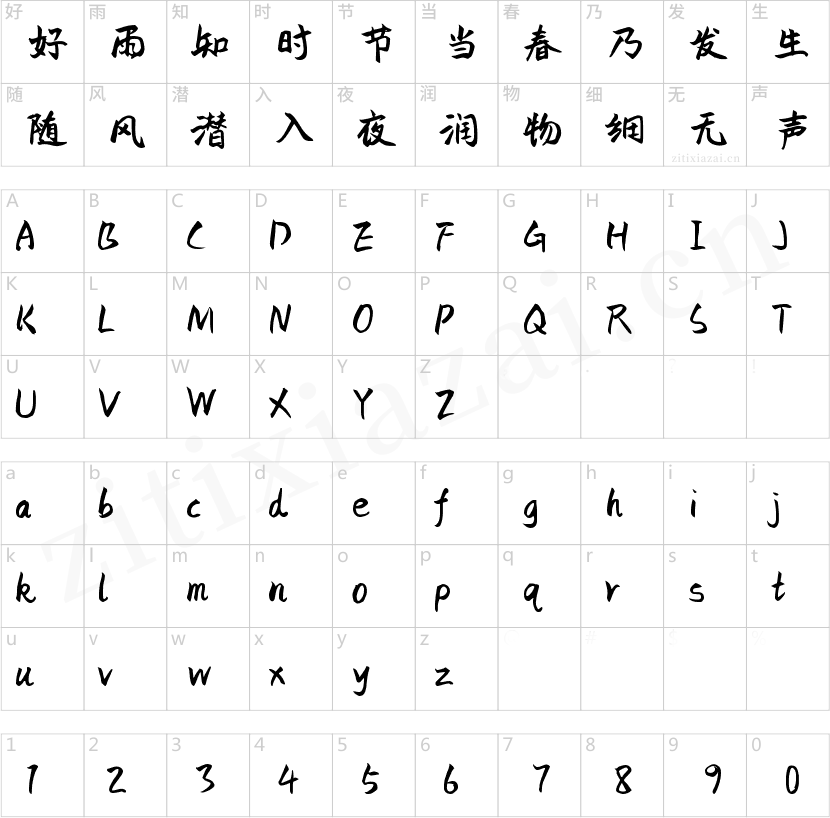
Aa晚风
Aa晚风字体
Aa晚风是一款非常具有艺术性的字体,它的设计灵感来源于对古典艺术的研究,同时又融入了现代字体设计的元素。字形优美,笔画粗细变化自然,给人以大气、典雅的感觉。Aa晚风是一款既传统又现代的字体,它的设计充满艺术感,美观大方,实用性也非常强。无论是对于设计师还是对于普通读者来说,都是一种非常不错的字体选择。Aa晚风适合用于具有艺术感的场合,比如海报、宣传单张、书籍封面等。由于其字形流畅且具有动态感,也适合用于大量的文本排版,如报纸、杂志等。